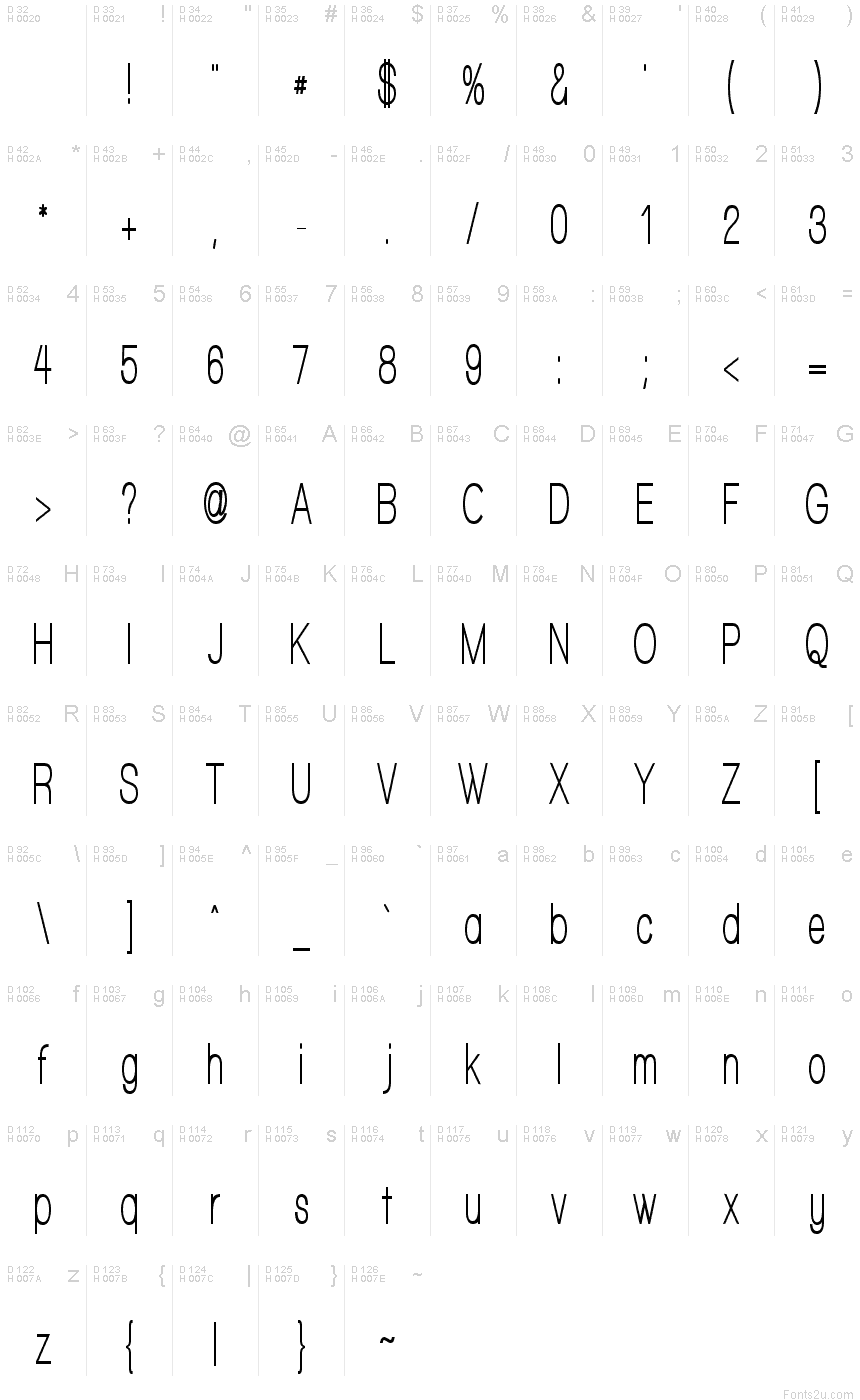
Walkway UltraCondensed Bold
Walkway UltraCondensed Bold di G.M. è un font sans serif ultra-condensato gratuito, dal tratto essenziale e moderno. Le lettere si sviluppano in tratti alti e stretti con pochissimi ornamenti, conferendo al carattere un ritmo elegante che appare più architettonico che neutro.
Si adatta perfettamente a qualsiasi contesto in cui serva una voce verticale e urbana per strutturare la pagina: poster, testate di moda, packaging, titoli e branding ispirato alla segnaletica sono tutti ambiti adatti al suo incedere compresso. Essendo un font gratuito, è particolarmente indicato per titoli brevi, testi di copertina e bozzetti di loghi, dove la sua altezza ridotta permette di inserire molte parole senza perdere quello stile pulito ed essenziale.